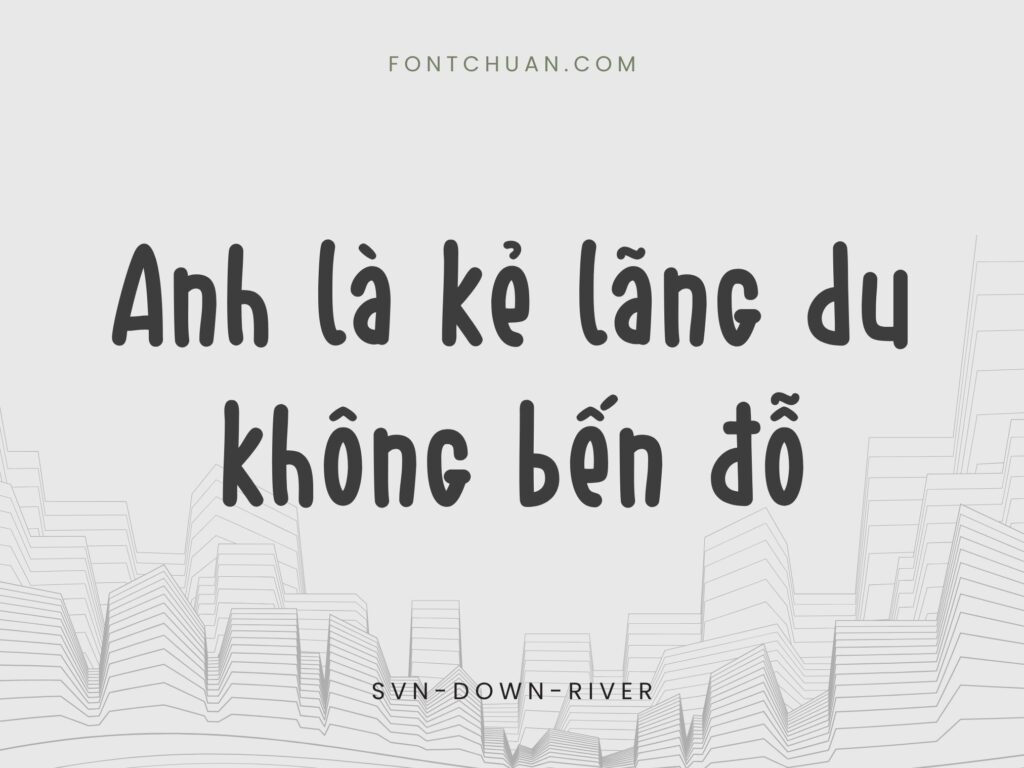
Font SVN Down River Việt Hóa
Font SVN Down River là phiên bản Việt hóa của kiểu chữ Down River, được thực hiện bởi Styleno.1 Fonts. Down River là một kiểu chữ viết tay ngọt ngào và nổi bật, tạo cảm giác tự nhiên và thân thiện. Font này thích hợp cho nhiều mục đích sử dụng khác nhau, từ thiết kế thiệp mời, logo đến các ấn phẩm truyền thông.
SVN Down River lý tưởng cho các dự án thiết kế yêu cầu sự cá nhân hóa và sáng tạo, như thiệp mời, logo và các ấn phẩm truyền thông. Các ngành nghề như thiệp cưới, ẩm thực và spa có thể tận dụng font này để tạo điểm nhấn trong thiết kế. Ngoài ra, font cũng thích hợp cho các sự kiện như Tết, Valentine, Sinh nhật và các lễ hội khác.